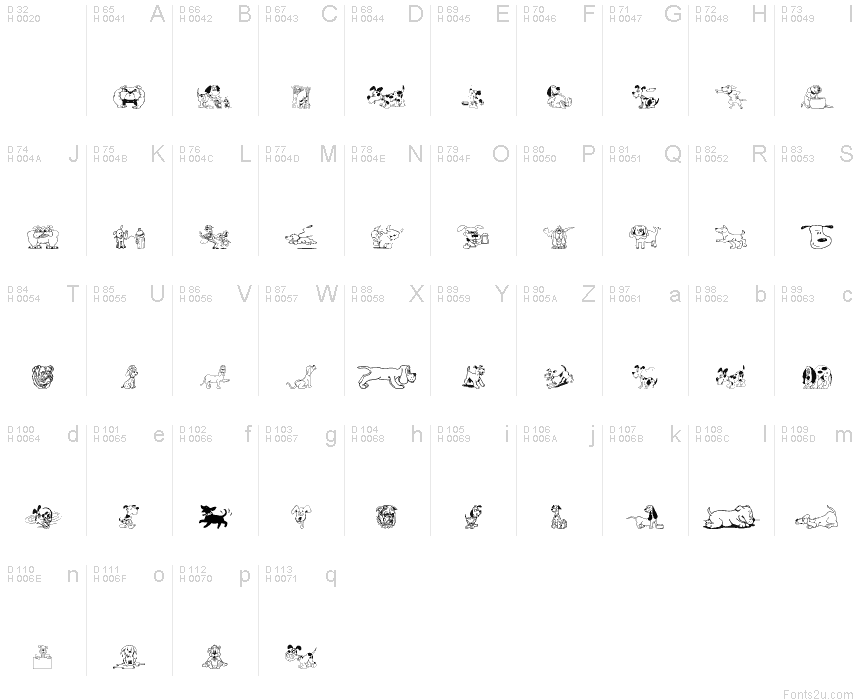
Doggon od GemFonts98 to darmowy font dingbats z psią tematyką. Jego szkicowe szczeniaki – łaciate, kudłate, z klapniętymi uszami, a nawet jeden wyglądający zza krawędzi – wnoszą ten rodzaj zabawnego uroku, który od razu mówi: to jest dla projektów miłośników psów, a nie jako generyczny zamiennik klipartów.
Doggon sprawdza się znakomicie w brandingu sklepów zoologicznych, ulotkach dla groomerów, plakatach imprez adopcyjnych, zaproszeniach na przyjęcia dla dzieci, zestawach naklejek, stronach do scrapbookingu, postach w mediach społecznościowych i oznakowaniu kojców. Połącz ten darmowy font z czystym, zaokrąglonym bezszeryfowym krojem pisma i daj ikonom sporo przestrzeni, aby ich radosny, merdający charakter pozostał czytelny.